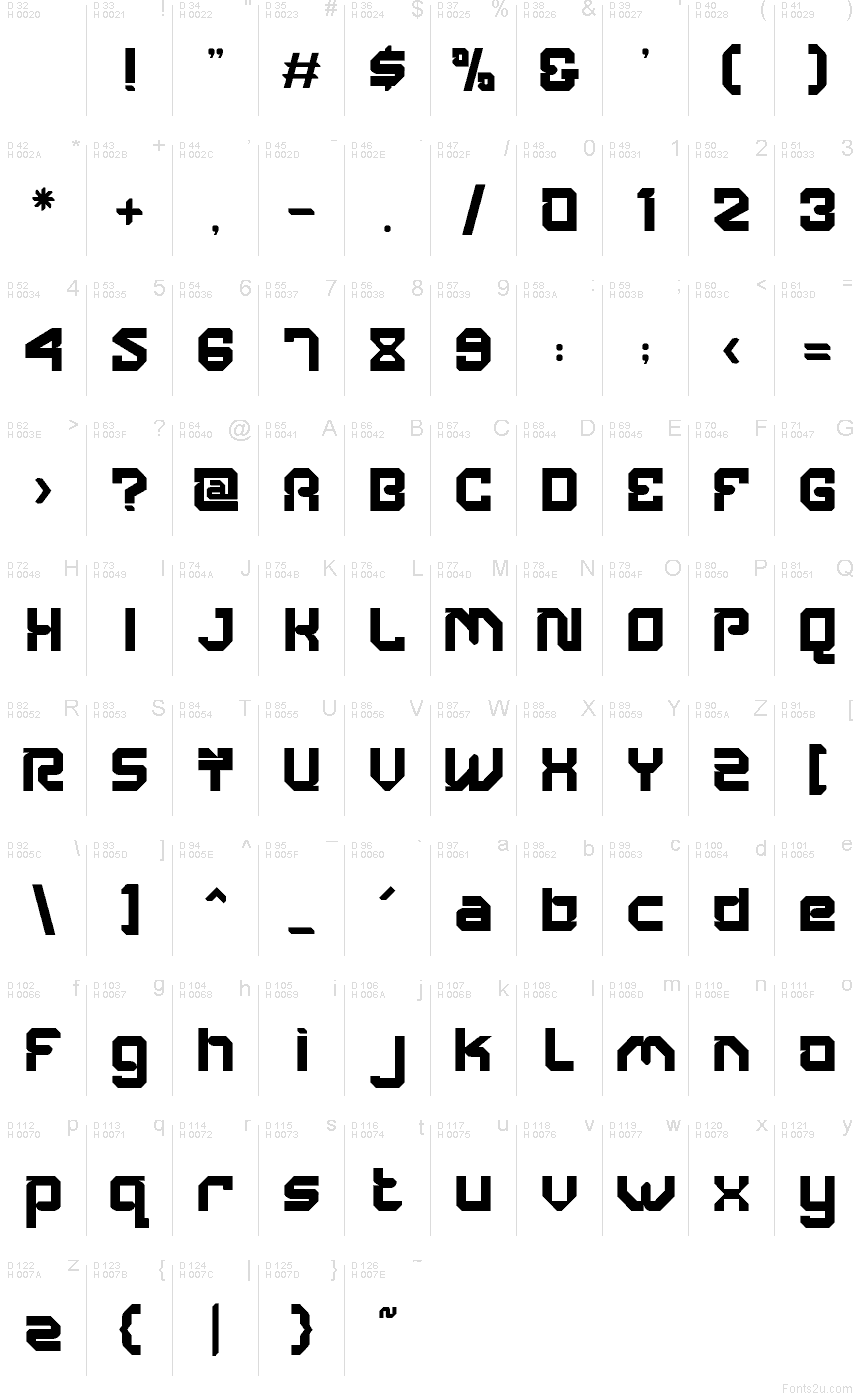
Cyber Crown od Putracetol Studio je bezplatné, futuristické bezpatkové písmo typu display, definované svou masivní strukturou a ostrými diagonálními řezy, díky nimž znaky působí, jako by byly vytvořeny z digitální mřížky. Kompaktní a propojená silueta dodává písmu úderný rytmus, kde uzavřené tvary a seříznuté rohy definují styl mnohem více než jakékoli povrchové efekty.
Hodí se do herních titulů, sci-fi plakátů, e-sport brandingu, streamovacích overlayů i titulků technologických akcí, protože toto písmo působí spíše jako písmena z uživatelského rozhraní než jako neutrální dekorativní typ. Své místo si najde i na obalech alb či designech obalů, kde tyto ostré úhly a husté tvary okamžitě signalizují syntetický, digitální tón.